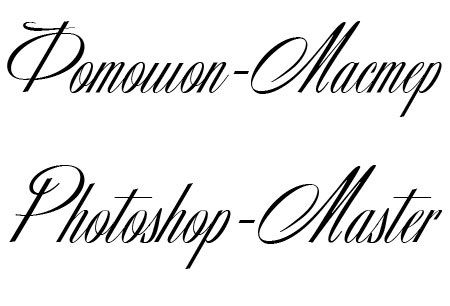
Красиво, спасибо!
Классненько, для комикса сойдет
Довольно богатый набор. Спасибо!
Великолепно
ЗдОрово! В коллекцию.
красивый шрифт :)
Спасибо. Красиво.
Булоб не погано як би і Українську підтримував
А русские буквы пишет? А то уменя некоторые шрифты только на англ. пишут!!!
Вы смотрите на скриншот,и читайте описание.Если на скриншоте написано на двух языках,значит на двух и пишет.